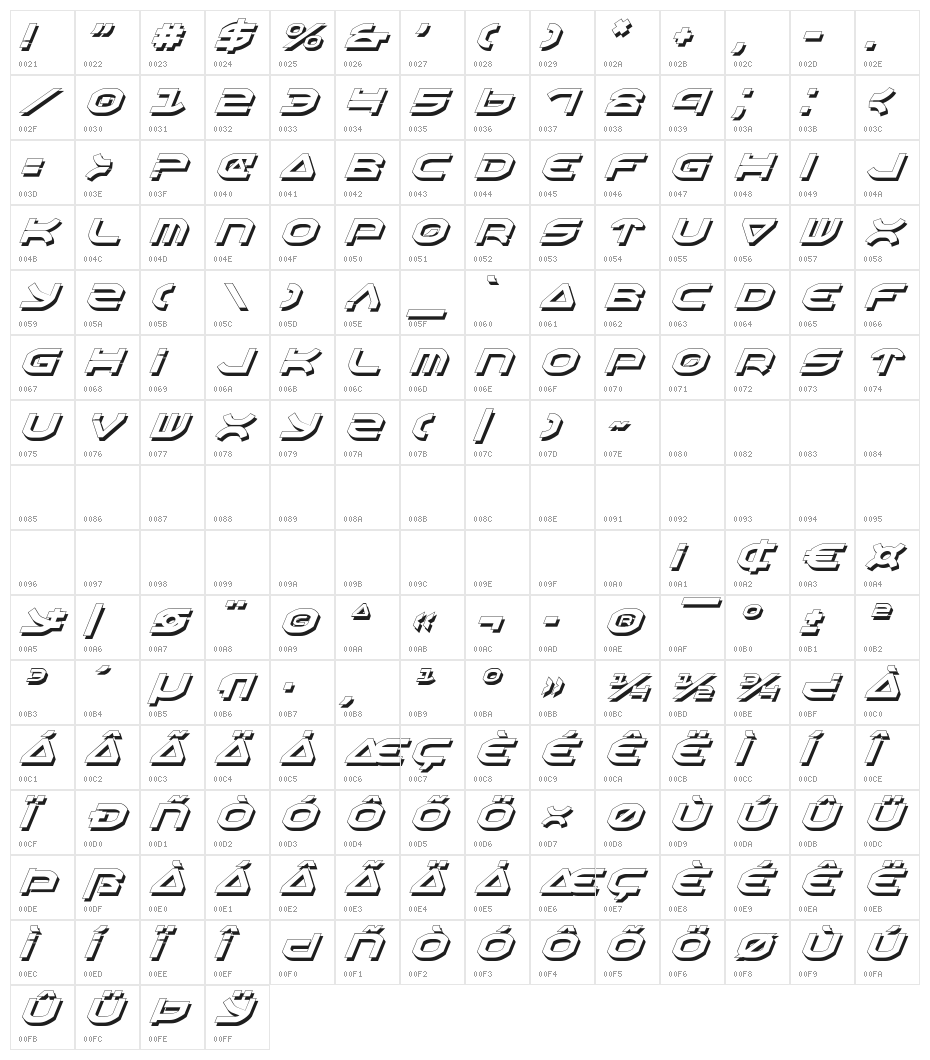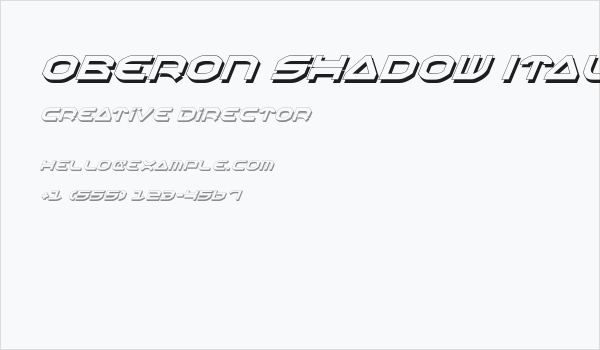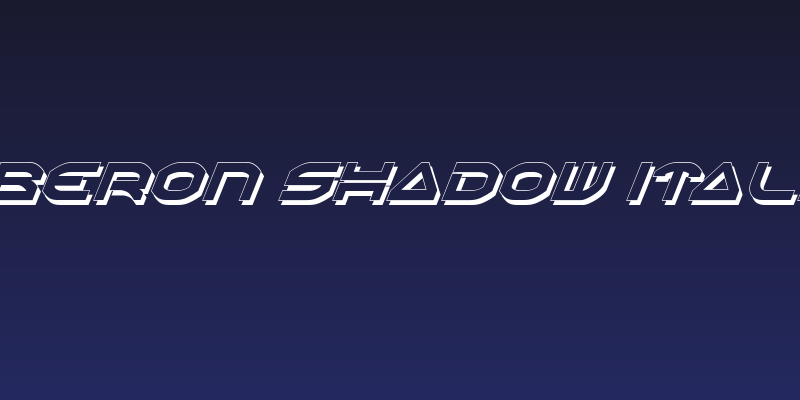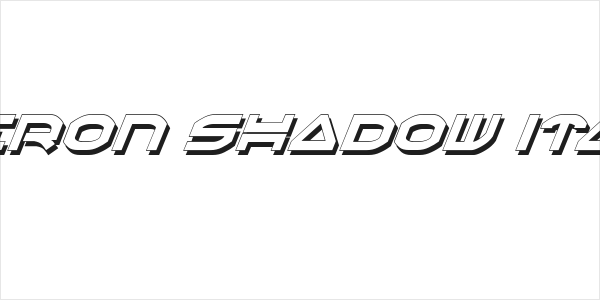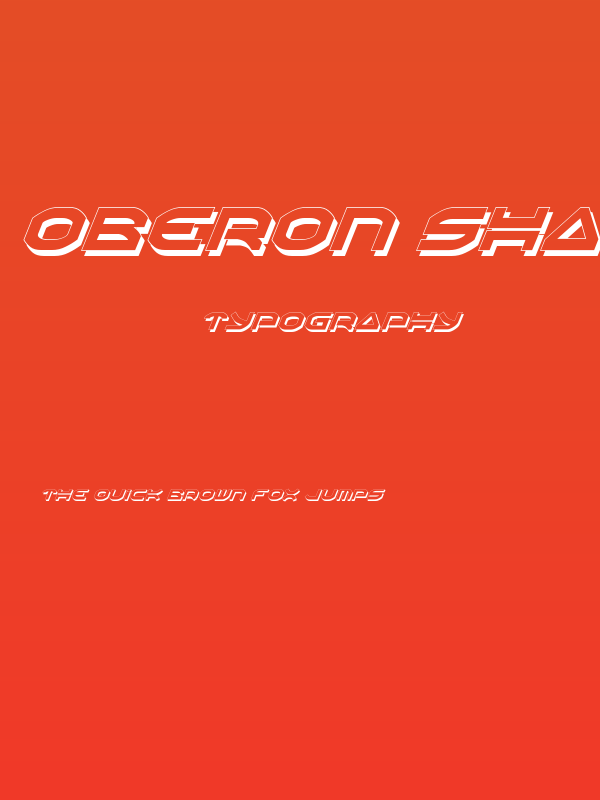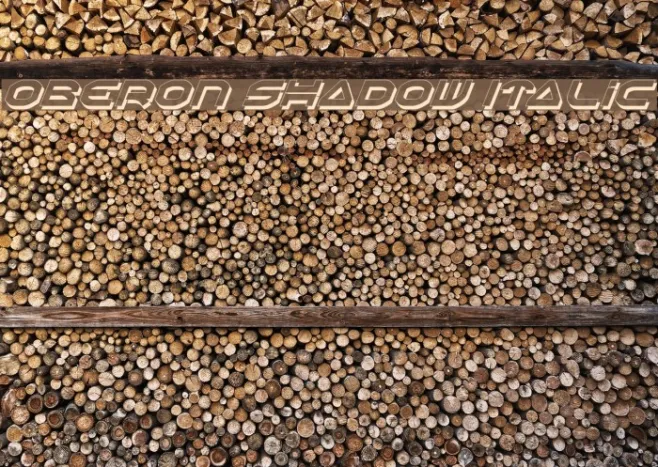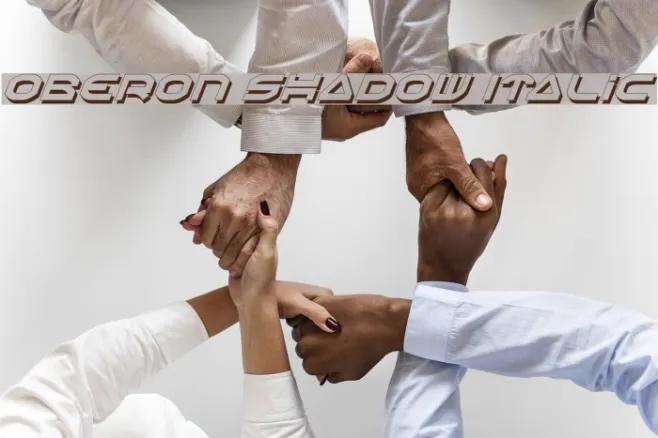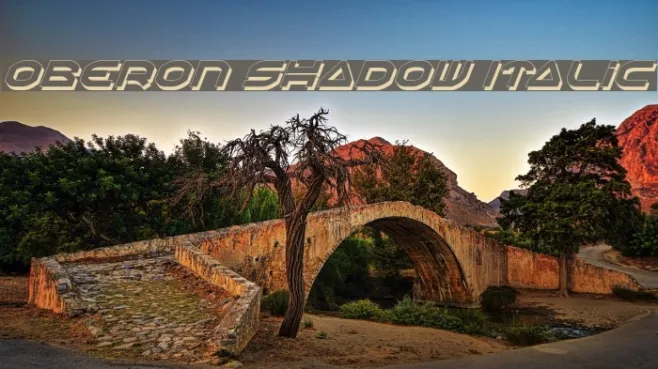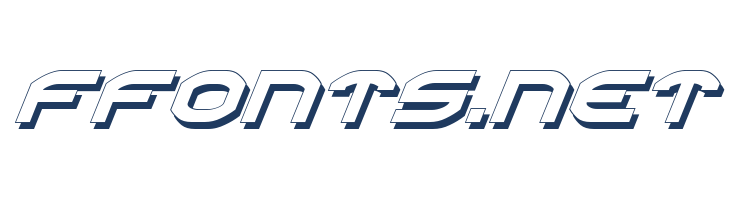
Oberon Shadow Italic Font
| Vorgeschlagene Projekte | Ideal for sci-fi themed designs, video game titles, posters, and branding that requires a modern and dynamic appearance. |